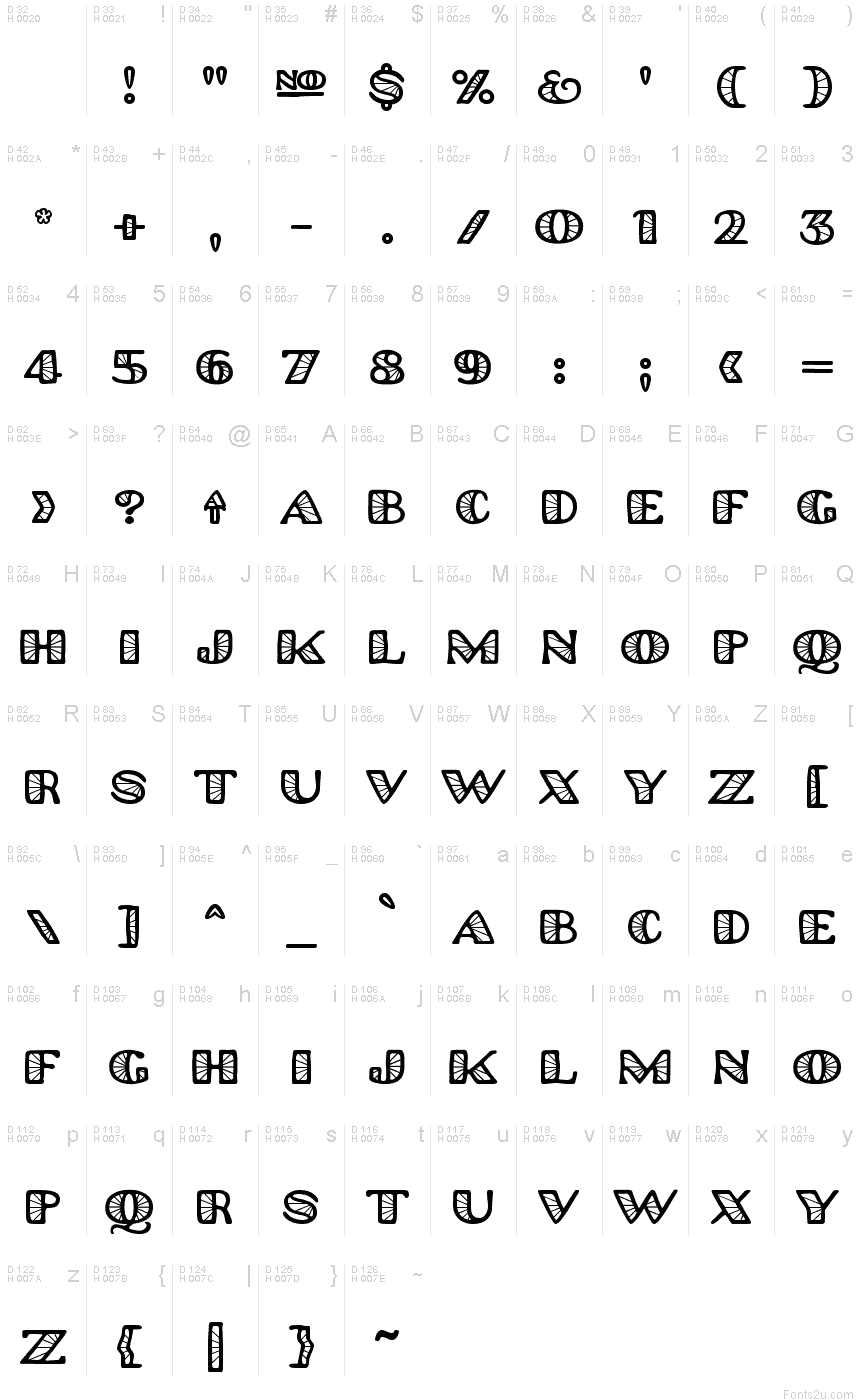
Platinum Hub Caps Spoked
Platinum Hub Caps Spoked autorstwa R. Gast to darmowy krój typu display o motoryzacyjnym charakterze w stylu hot-rod. Litery są ciężkie i zaokrąglone, a każda z nich wyrzeźbiona z klinami i szprychami przypominającymi kołpaki, dzięki czemu alfabet wygląda jak grafika chromowanych felg przeniesiona na szyldy.
Doskonale pasuje do logotypów warsztatów, ulotek ze zlotów samochodowych, plakatów warsztatowych, menu w stylu retro czy plansz tytułowych dla wszystkiego, co związane z kulturą custom. Jako darmowy font najlepiej sprawdza się tam, gdzie litery mogą pozostać duże i zwięzłe – w nagłówkach okładek, monogramach i krótkich tytułach – ponieważ ten powtarzalny motyw koła sam w sobie przyciąga wzrok.